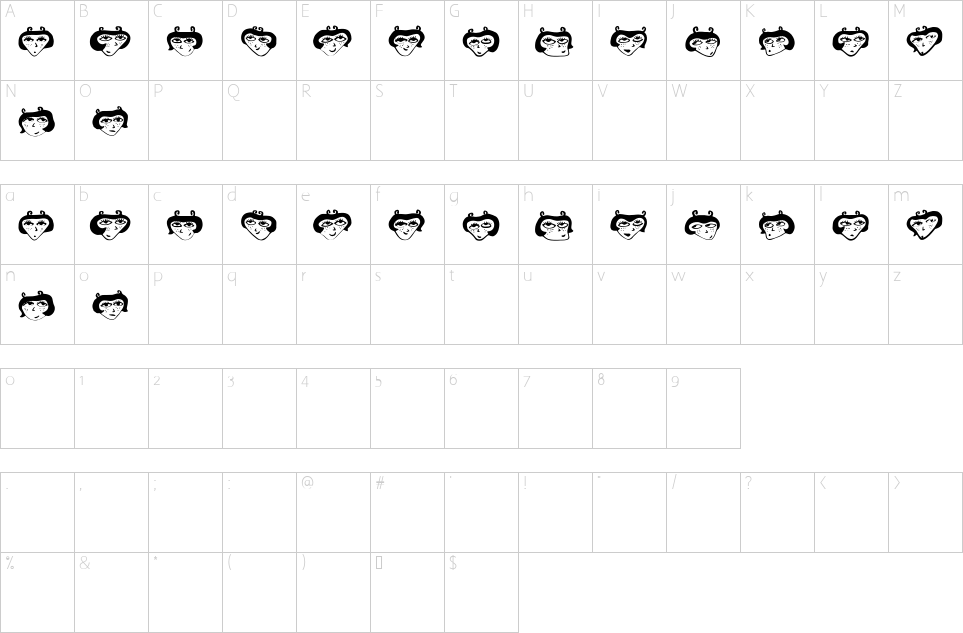
Anichka é uma fonte de design minimalista e elegante criada por Vladimir Nikolic. Esta fonte tem sido muito apreciada por designers de todos os níveis, desde iniciantes até profissionais experientes. Seu estilo arredondado e alegre torna-a uma escolha ótima para aplicativos pessoais e pequenos projetos, bem como para criações mais complexas que requerem um toque único. Com seus 2,410 downloads, é evidente que designers do mundo todo valorizam os benefícios deste design minimalista e criativo. Anichka é uma escolha perfeita para aqueles que buscam uma fonte ligeiramente distinta, sem perder a simplicidade e a praticidade que tanto apreciamos em nossos designers digitais. Sem dúvida, é uma fonte grátis que merece ser descoberta e utilizada em seu próximo projeto.